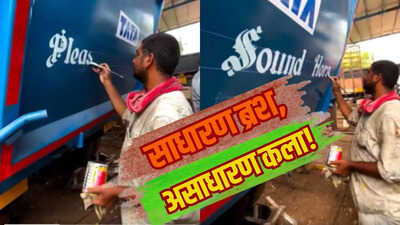
भारत में हुनर की कोई कमी नहीं है। यहां ऐसे-ऐसे कलाकार हैं, जो अपनी कला से लोगों को हैरान कर देते हैं। इन दिनों सोशल मीडिया पर एक ऐसा ही वीडियो काफी तेजी से वायरल हो रहा है, जिसमें एक पेंटर अपने शानदार हुनर से लोगों को हैरानी में डाल दे रहा है। इस वीडियो को देखने के बाद हर कोई उस पेंटर की कला की तारीफ कर रहा है।
पेंटर ने लिखी कंप्यूटर जैसी लिखावट
इस वीडियो (Video) को सोशल मीडिया प्लेटफॉर्म X पर @Rainmaker1973 (Massimo) नाम के अकाउंट से शेयर किया गया है। पोस्ट के साथ सिर्फ इतना लिखा गया है, "Font-like Indian calligraphy." वीडियो में देखा जा सकता है कि एक कलाकार नीले रंग के टाटा ट्रक पर सफेद पेंट और ब्रश की मदद से बेहद ही खूबसूरत अक्षर में "Please Sound Horn" लिखते हुए दिख रहा है। इस वीडियो में सबसे खास बात यह है कि उसकी लिखावट बिल्कुल किसी कंप्यूटर फॉन्ट जैसी दिखाई देती है। हर अक्षर एक जैसा, साफ और बेहद सुंदर नजर आता है।
कलाकार के हुनर का कमाल देख हर कोई कर रहा तारीफ
सबसे हैरानी की बात यह है कि कलाकार इन शब्दों को लिखने के लिए किसी स्टेंसिल या मशीन का इस्तेमाल नहीं करता। वह केवल अपने हाथ, ब्रश और सालों के अनुभव के दम पर इतनी शानदार कैलिग्राफी तैयार कर देता है। उसकी ब्रश चलाने की स्पीड और अक्षरों की सटीक बनावट देखकर लोग हैरान रह जाते हैं। इस वीडियो में कलाकार का हुनर देख लोगों ने जमकर अपनी प्रतिक्रिया दी है। कई यूजर्स ने लिखा कि यह सिर्फ लिखावट नहीं, बल्कि एक शानदार कला है। कुछ लोगों ने कहा कि अगर यही काम कंप्यूटर से किया जाता, तो शायद इतना सुंदर नहीं लगता। वहीं कई लोगों ने भारतीय ट्रक कलाकारों के हुनर को सलाम किया।